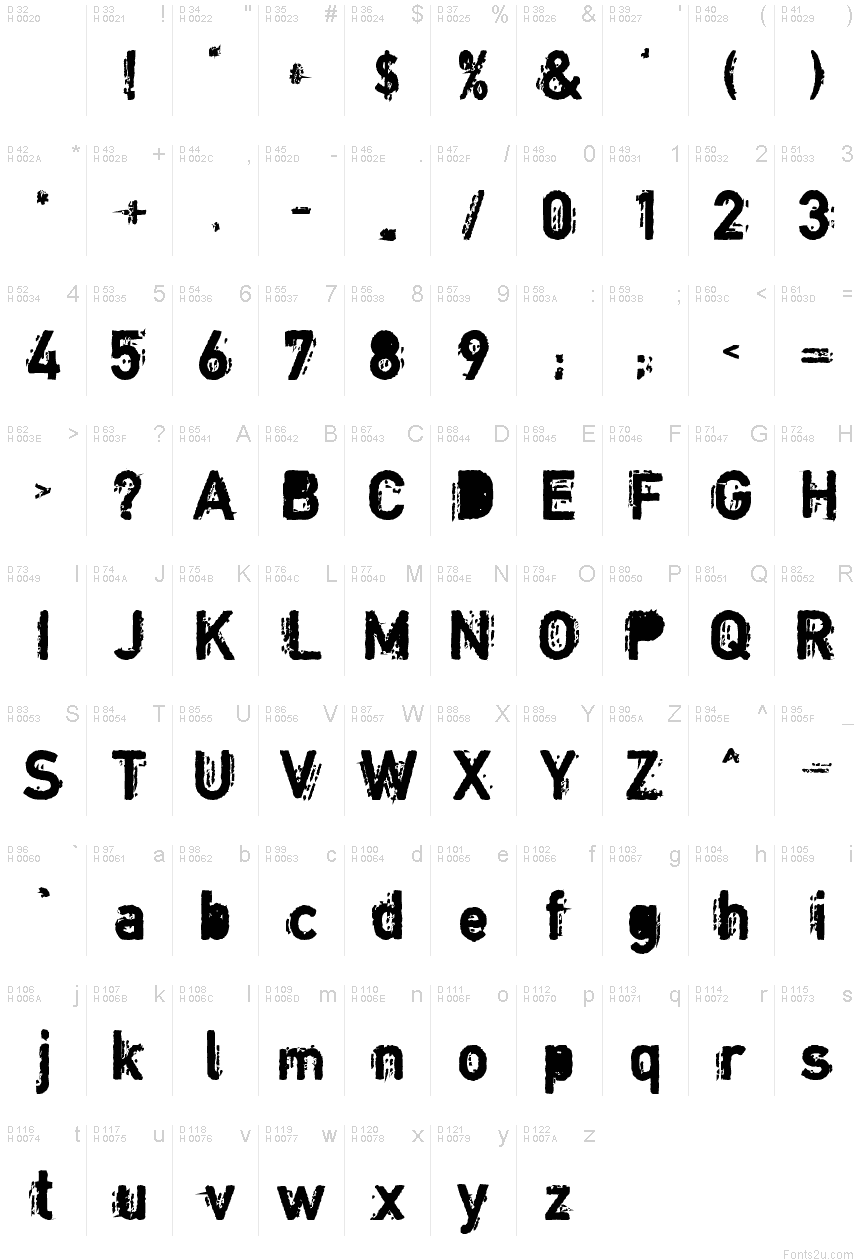
Copystruct Bold من Typografski هو خط للعناوين (ديسبلاي) مجاني بتصميم متآكل، يبدو وكأنه مرّ عبر آلة تصوير مستندات مرات كثيرة جداً. تتفتت الحواف في الأشكال السوداء السميكة لتتحول إلى بقع وخطوط، مما يمنح عائلة Copystruct طاقة خاماً وصناعية ومشبعة بالحبر. تظل الحروف قوية وسهلة القراءة، لكنها تحمل طابعاً مهترئاً وجسدياً يشبه جدران المستودعات.
باستخدام Copystruct Bold، يمكنك إضفاء لمسة خشنة على ملصقات الحفلات، والمنشورات الاحتجاجية، وعناوين أفلام الرعب، والمجلات المستقلة، وأغلفة الألبومات دون فقدان الوضوح. هذا الخط المجاني يتألق عند استخدامه بأحجام كبيرة حيث تظهر حبيباته وتمزقاته بوضوح؛ قم بإقرانه بخط بلا زوائد (sans-serif) ضيق ونظيف للنص الأساسي للحفاظ على وضوح وقراءة المحتوى المحيط.